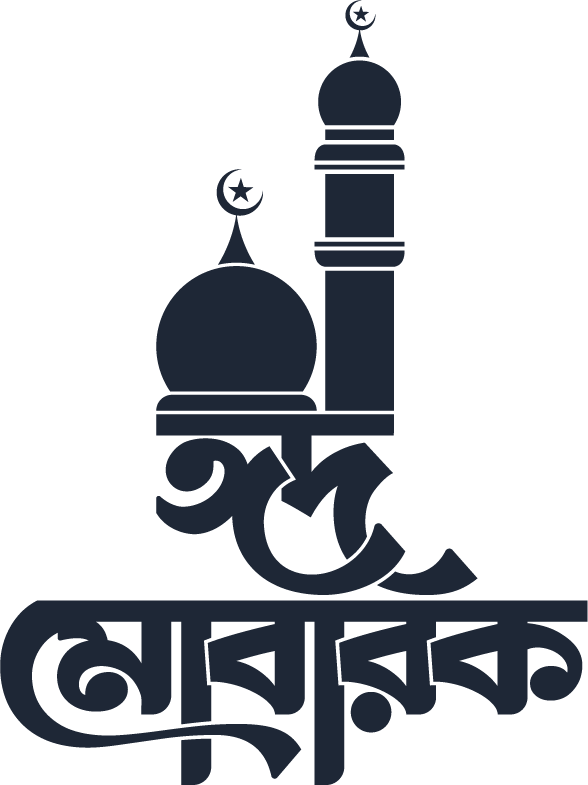
ঈদ মোবারক ক্যালিগ্রাফি বাংলা – ক্যালিগ্রাফি বাংলা ফন্ট ডিজাইন
ঈদ মোবারক ক্যালিগ্রাফি বাংলা হলো অত্যন্ত সুন্দর একটি বাংলা ক্যালিগ্রাফি (Bangla Calligraphy)। যারা ইসলামিক ডিজাইন, ব্যানার, পোস্টার বা ওয়েবসাইটের জন্য প্রফেশনাল ক্যালিগ্রাফি খুঁজছেন, তাদের জন্য ঈদ মোবারক ক্যালিগ্রাফি বাংলা একটি দারুণ পছন্দ।
ক্যালিগ্রাফির বৈশিষ্ট্য ও ব্যবহার:
- ডিজাইনের নাম: ঈদ মোবারক ক্যালিগ্রাফি বাংলা
- ব্যবহারক্ষেত্র: ব্যক্তিগত প্রজেক্ট, থাম্বনেইল ডিজাইন, ব্যানার এবং ক্যালিগ্রাফি আর্টওয়ার্ক।